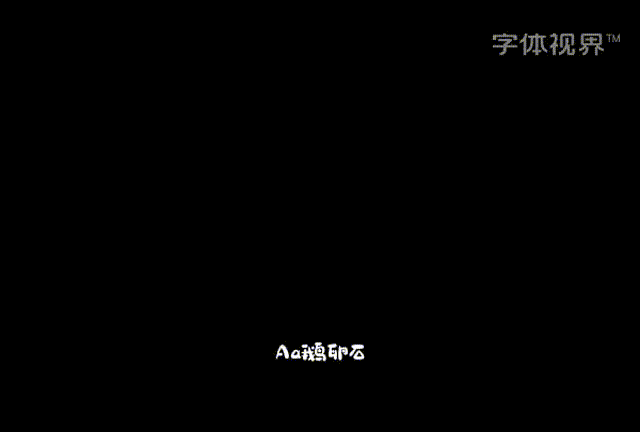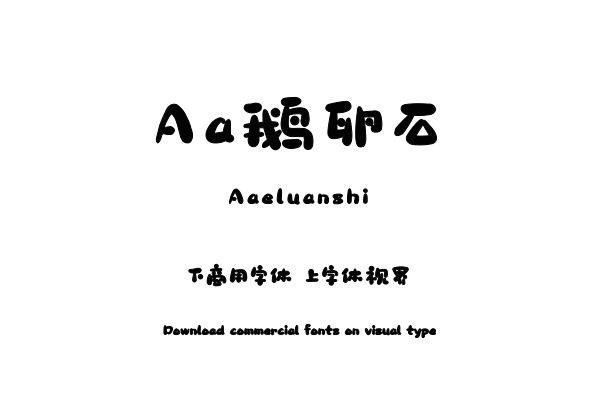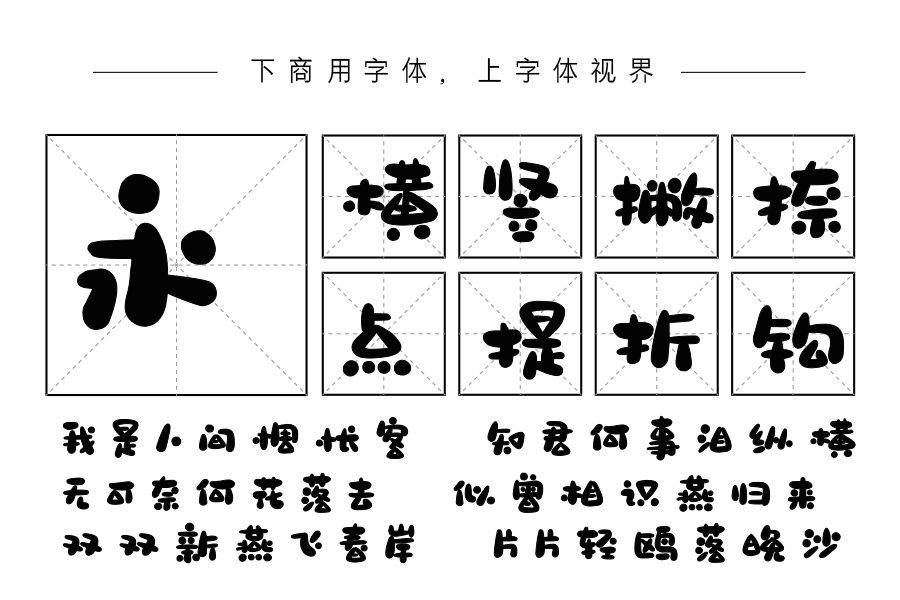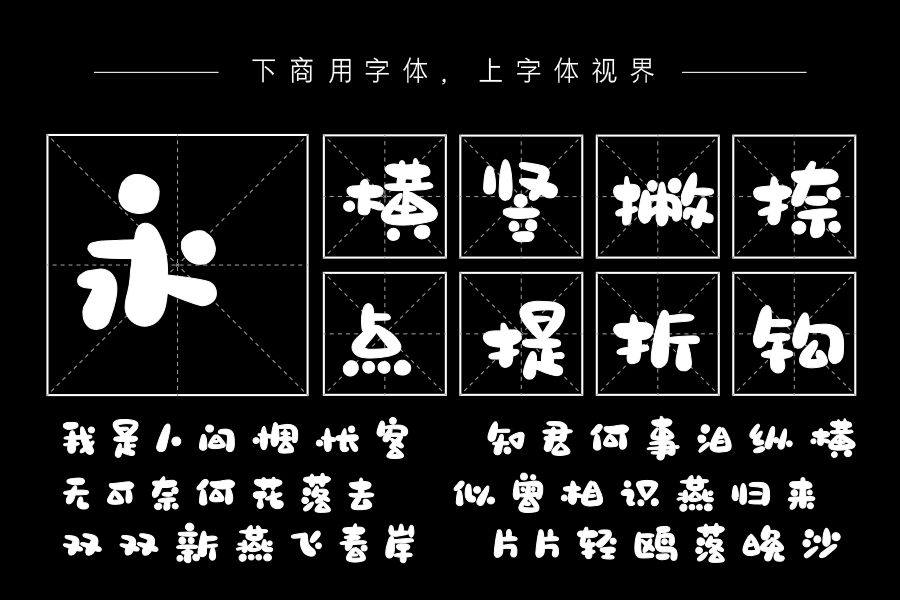
不仅口等封闭部件呈三角形,一头宽一头窄的笔画也都是圆润的三角形,如同鹅卵石的堆叠,可爱有趣,充满卡通感。购买须知:“下载服务费”与“字体VIP”所获得字体 仅用于个人非商用, 商用请联系付费授权。本字体为电脑用字,手机没有root权限不支持直接手机换字(手机如何root,请自行百度搜索教程)。购买前请先 了解清楚后再付款 ,字体为虚拟产品无法回收 一旦购买不支持退款。